유명 브랜드의 로고를 보면 단순하면서도 강렬한 디자인을 가지고 있어요. 싸인도 마찬가지로, 눈에 띄면서 기억에 남는 디자인이 중요하죠. 그럼 세계적인 브랜드 로고에서 싸인 디자인에 활용할 수 있는 팁을 배워볼까요? 🚀
브랜드 로고와 싸인의 공통점 🖊
브랜드 로고는 기업의 정체성을 나타내고, 싸인은 개인의 아이덴티티를 표현하는 역할을 해요. 그렇다면 로고와 싸인은 어떤 공통점이 있을까요? 🤔
🔍 로고와 싸인의 공통 요소 💡
공통점 설명 간결함 단순하면서도 강한 인상을 주는 것이 중요해요. 독창성 다른 사람과 차별화된 디자인이어야 해요. 가독성 빠르게 보아도 쉽게 읽히고 이해할 수 있어야 해요. 아이덴티티 자신만의 개성과 스타일을 담아야 해요. 이제 브랜드 로고에서 배우는 디자인 원칙을 활용해 싸인을 더 멋지게 만들어볼까요? 😊
심플한 디자인이 강력한 이유 ✨
브랜드 로고를 보면 대부분 심플하면서도 강렬한 디자인을 가지고 있어요. 싸인도 마찬가지로, 복잡하지 않지만 개성이 살아 있어야 기억에 남죠! 그럼 심플한 디자인이 왜 강력한지 알아볼까요? 🤔
🎯 심플한 싸인의 장점 🖊
장점 설명 빠르게 작성 가능 서류 작성 시 시간을 단축할 수 있어요. 기억하기 쉬움 단순할수록 상대방이 쉽게 기억할 수 있어요. 위조 방지 적당한 독창성이 있어야 위조가 어렵죠. 스타일리시한 느낌 군더더기 없이 깔끔한 싸인은 세련돼 보여요. 이제 심플한 디자인의 중요성을 알았어요. 그렇다면 싸인에 개성을 넣는 방법을 알아볼까요? 😆
개성 있는 스타일 만들기 🎨
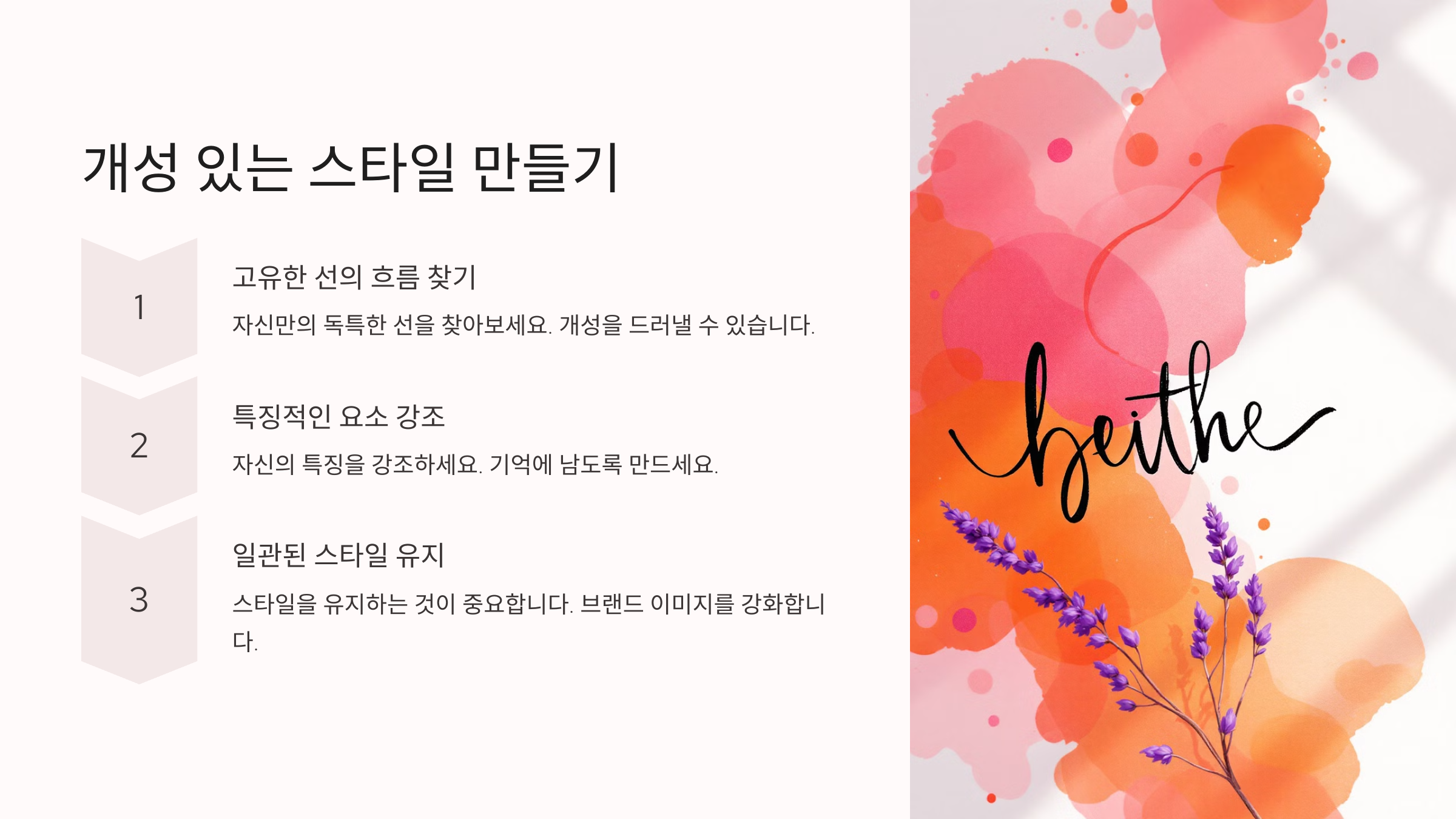
싸인은 나만의 개성을 담아야 해요. 너무 흔한 디자인보다는, 조금만 변형해도 확실한 차별점이 생기죠! 그럼 개성을 살리는 요소들을 살펴볼까요? 🤩
🔹 싸인에 개성을 더하는 3가지 방법 🔥
- 이니셜 강조 → 이름의 첫 글자를 크게 쓰면 개성이 살아나요.
- 특별한 기호 추가 → 별 ⭐, 점 . , 밑줄 __ 등을 활용해 보세요.
- 획의 강약 조절 → 굵은 선과 얇은 선을 섞으면 스타일리시해요.
이렇게 개성을 살린 싸인을 만들면 더 멋져 보이겠죠? 😎 이제 싸인을 디자인할 때 균형을 맞추는 방법을 알아볼까요?
균형 잡힌 싸인 디자인 ⚖
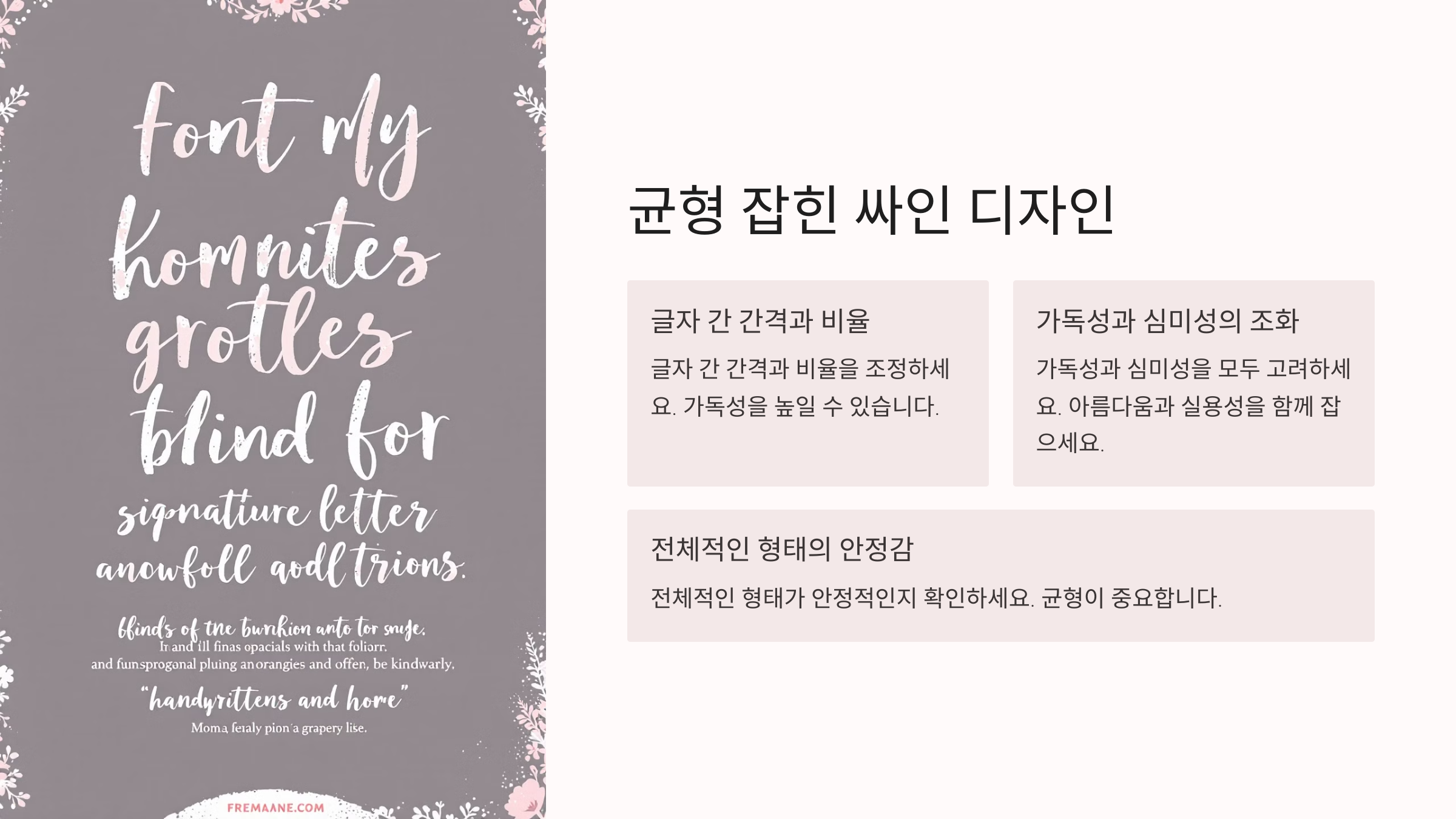
싸인은 균형이 맞아야 보기 좋아요. 너무 기울거나 삐뚤어진 형태는 가독성이 떨어질 수 있죠. 그럼 싸인을 디자인할 때 균형을 맞추는 방법을 알아볼까요? 🤓
📌 균형 잡힌 싸인을 위한 3가지 원칙 ✅
- 너무 길지 않게 → 한 줄에 적당한 길이가 가장 보기 좋아요.
- 적당한 기울기 유지 → 너무 기울어지면 가독성이 떨어질 수 있어요.
- 공간 활용 → 글자 간격이 너무 붙거나 떨어지지 않도록 조절하세요.
이제 싸인의 균형을 맞추는 방법도 배웠어요. 그럼 브랜드 로고처럼 싸인에 특별한 기호를 활용하는 법을 알아볼까요? 😉
로고에서 활용하는 기호 & 요소 ✨
브랜드 로고에는 특별한 기호나 디자인 요소가 많이 들어가요. 이런 요소를 싸인에 적용하면 더 개성 있고 세련된 느낌을 줄 수 있어요! 😎 그럼 싸인에 활용할 수 있는 기호와 디자인 요소를 살펴볼까요? 🔍
🔹 싸인에 넣으면 좋은 기호 5가지 🖊
기호 설명 ⭐ 별 독창적이고 개성 있는 느낌을 줘요. ✔ 체크 자신감과 전문성을 강조할 수 있어요. _ 밑줄 이름을 강조하고 깔끔한 마무리를 할 수 있어요. . 점 디자인적으로 심플하지만 세련된 느낌을 줄 수 있어요. ↗ 화살표 성장과 발전하는 이미지를 표현할 수 있어요. 이제 싸인에 활용할 기호와 요소를 알았어요! 그럼 직접 나만의 싸인을 디자인하는 방법을 알아볼까요? 🤩
나만의 싸인 디자인하는 법 🎨
이제 배운 내용을 활용해 나만의 싸인을 디자인해 볼 차례예요! 브랜드 로고에서 배운 요소들을 적용하면 싸인이 더욱 멋지게 변할 거예요. ✍
🖊 5단계 싸인 디자인 과정 🔥
단계 설명 STEP 1: 기본 구조 정하기 이름 전체 또는 이니셜을 활용해 기본적인 형태를 만들어요. STEP 2: 스타일 결정 곡선, 직선, 기울기 등을 선택해서 디자인 방향을 정해요. STEP 3: 기호 추가 별 ⭐, 밑줄 _, 점 . 등을 넣어 개성을 더해요. STEP 4: 균형 맞추기 글자 간격, 기울기 등을 조절해 시각적으로 안정적인 디자인을 완성해요. STEP 5: 반복 연습 자연스럽게 싸인이 손에 익도록 여러 번 써보며 연습해요. 이제 여러분도 나만의 개성 있는 싸인을 만들 준비가 되었나요? 😆 마지막으로 싸인과 관련된 궁금증을 해결해 볼까요? ❓
FAQ ❓
Q1. 싸인을 만들 때 브랜드 로고처럼 디자인해도 되나요?
A1. 네! 브랜드 로고처럼 단순하면서도 개성 있는 디자인을 만들면 좋아요.
Q2. 싸인에 색상을 넣어도 될까요?
A2. 일상적인 싸인은 보통 검은색이나 파란색을 쓰지만, 디자인적인 요소로 색상을 활용하면 개성을 더할 수 있어요! 🎨
Q3. 싸인에 기호를 너무 많이 넣으면 안 좋을까요?
A3. 네, 기호는 한두 개 정도만 넣어야 가독성을 유지할 수 있어요. 너무 많으면 싸인이 복잡해 보일 수 있어요. 😉
Q4. 싸인 연습을 많이 해야 하나요?
A4. 네! 하루 5~10분 정도 연습하면 자연스럽게 손에 익어요. 자연스럽게 나오도록 반복 연습하는 것이 중요해요! 🖊
Q5. 싸인을 바꾸면 법적으로 문제 될까요?
A5. 아니요! 하지만 공식 서류에 사용하는 싸인은 변경 시 신고해야 할 수도 있어요. 은행 서류나 여권 등에 등록된 싸인은 일관성을 유지하는 것이 좋아요. 📜